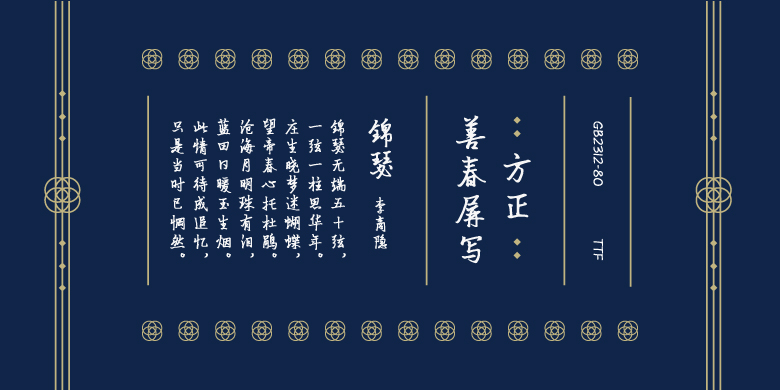
品牌:方正手迹 设计师:孙善春发行时间:2018字库编码:大陆简体(GB2312-80)、简繁扩展(GBK)分类:创意书写
作者:孙善春,艺名萧非,号“熊猫老师”。浙江大学德国哲学博士。现为中国美术学院教师,硕士研究生导师。
作者以屏为纸,以指为笔书就。这是力将书法的时空性带进字体的一个充满生机的探索。笔画柔韧老道,富有动势,结体和畅优美,气息儒雅。屏幕书写的文字经数字化转换后,笔画光洁而统一,数据量较小,其质感更彰显现代技术文明。而通过纸质书写再进行扫描的传统制作方式则难以达到这样的效果。需要特别指出的是,作者用了近5年的练习来掌握屏写技能,为在信息时代唤起人们对汉字审美关注,付诸可贵的行动。该字体适合于广告和网络应用,并能胜任个性化文本的排版。